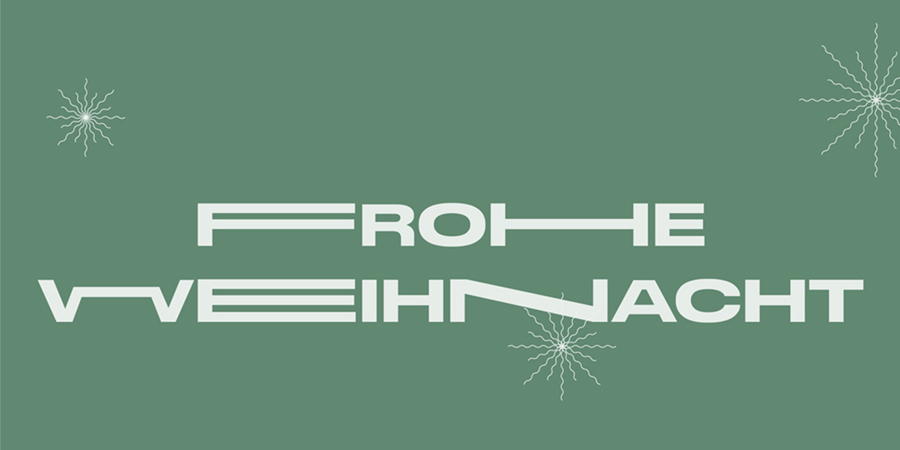
„Was ist deiner Meinung nach die weihnachtlichste Schriftart?“
Diese Frage stellte mir vor wenigen Wochen der Berufs- und Kreativverband Allianz deutscher Designer (AGD) e.V. in Berlin.
Meine Antwort: „Man kann Weihnachten mit Serifen, ganz linear oder mit flottem Federstrich begehen. Dieses Jahr wirkt Weihnachten auf mich so gezogen und gebogen, dass mir dazu nur der Font ‚Stretch Pro‘ einfällt.” Worauf ich die Antwort bekam: „… Weihnachten ist gerettet!“